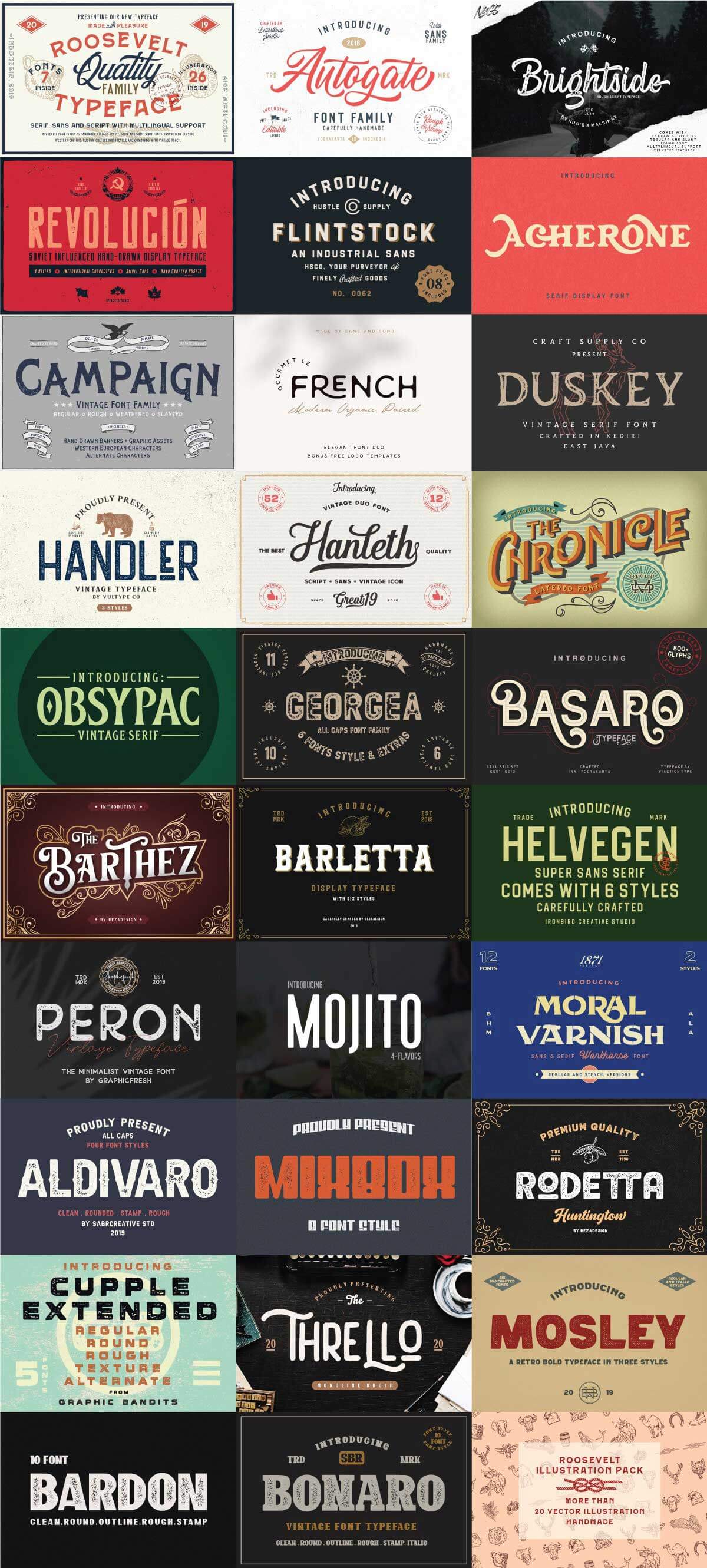
Pixel Surplusでは、フォント集「The Ultimate Vintage Font Collection(ザ・アルティメイト・ヴィンテージ・フォント・コレクション)」が一ヶ月限定販売中です。
かっこいいヴィンテージ書体29セットを収録したコレクションです。Pixel Surplusでしか買えないオリジナルフォントや、イラストやロゴテンプレートなどのおまけもたくさん入っています。
「The Ultimate Vintage Font Collection」の気になる内容
今回のバンドルの中で、私が特に気になるフォントはこちらです。
Gourmet Le French – Sans & Sons
インクが溜まったような表現がポイントの「Gourmet Le French」。ペアで使いたいスクリプトフォントと、ロゴ作成に便利なテンプレートつきです。
Acherone – Runsell Studio
用意された字形を組み合わせれば、おしゃれなロゴや見出しが簡単にできる「Acherone」。連字も多数用意されています。
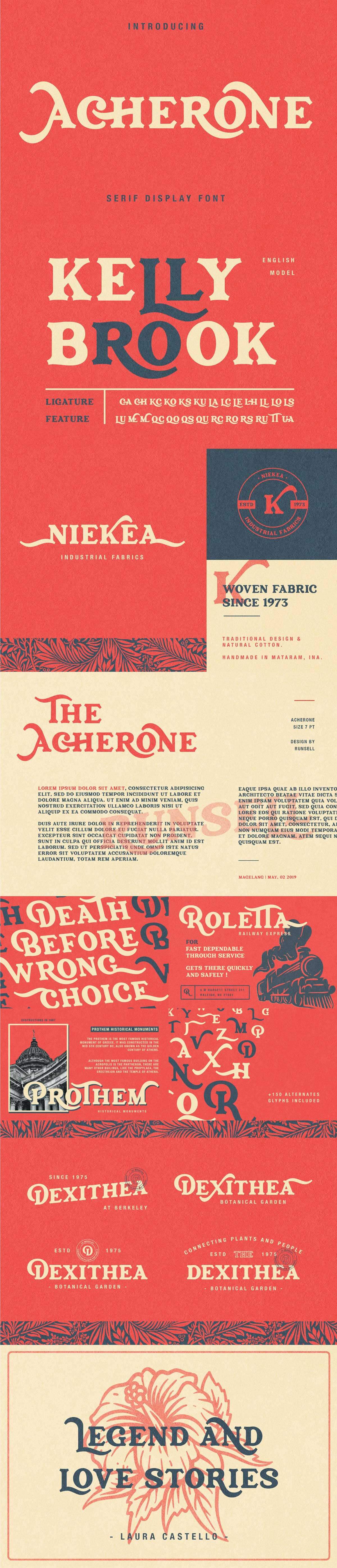
Hanleth – great19
便利なヴィンテージアイコンやロゴテンプレートつきの「Hanleth」。サンセリフ体とスクリプト体のセットになっています。
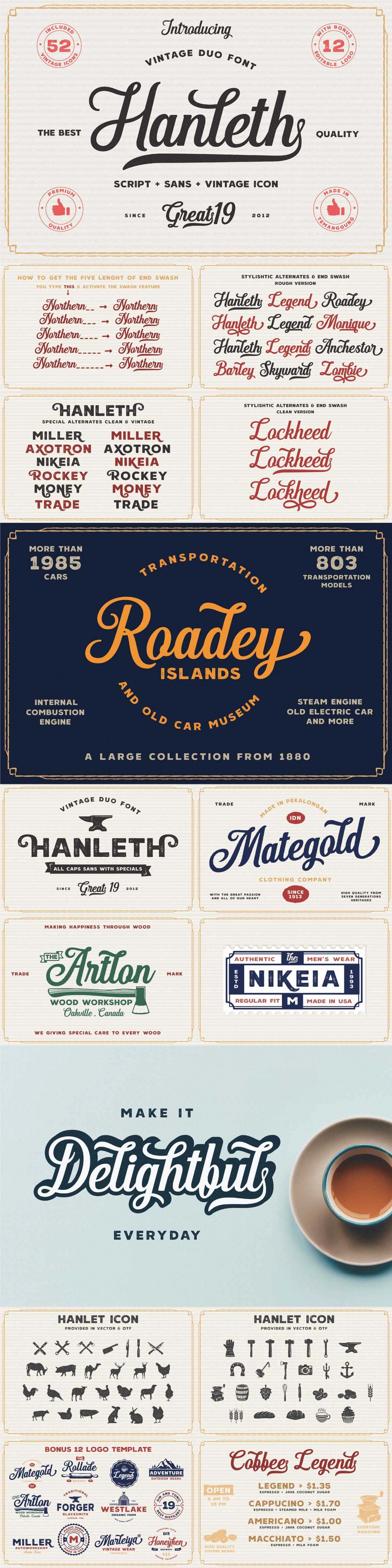
The Chronicle – MadeDeduk
装飾性の高い見出しやロゴも簡単に作成できる「The Chronicle」。重ねて使うのが前提で作られています。一緒に使いたいフレーム素材も充実しています。
Mojito – Pixel Surplus
Pixel Surplusオリジナルフォント「Mojito」。通常版とテクスチャ版の2種類にそれぞれイタリック体つきで、合計4書体収録されています。
このほか合計29セットを収録しています。この記事で紹介できなかった書体はぜひ詳細ページから確認してくださいね。